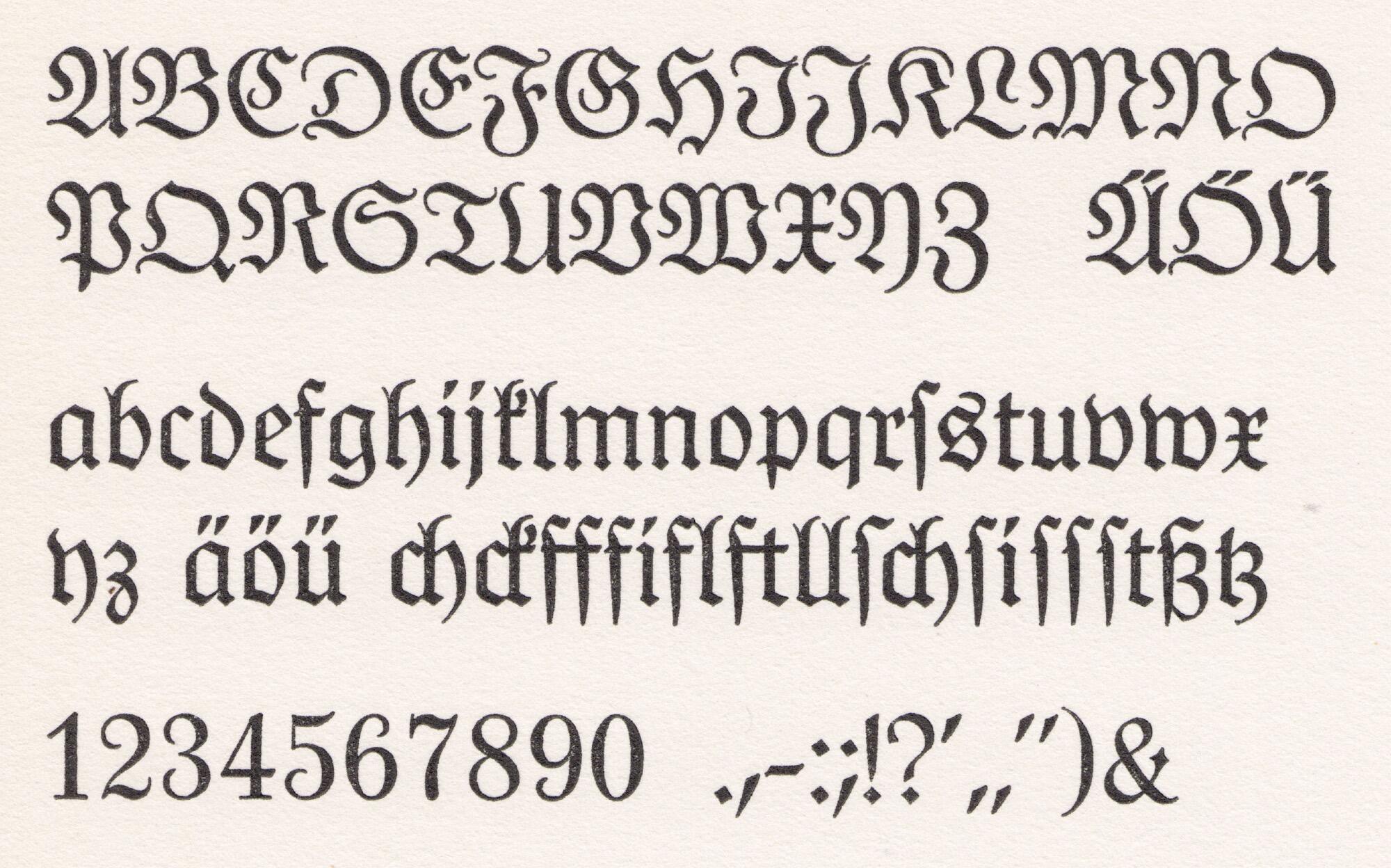
• 1934
• Gebrochene Schrift
Die Deutsche Werkschrift erschien 1934 in zwei Garnituren (mager/halbfett) als Ergänzung zur erfolgreichen Deutschen Anzeigenschrift von Rudolf Koch. Für den abweichenden Einsatz als Fließtextschrift erhielten die beiden Garnituren jedoch den abweichenden und besser passenden Namen Deutsche Werkschrift.